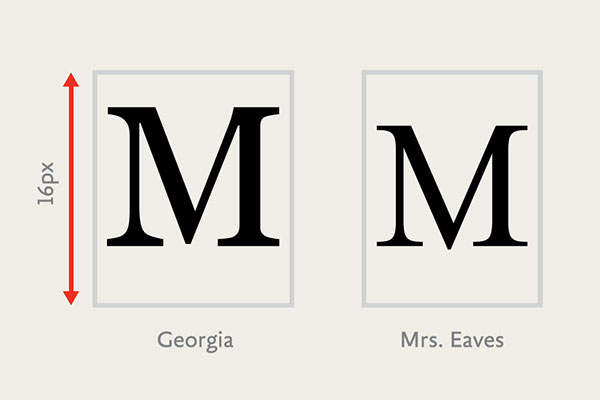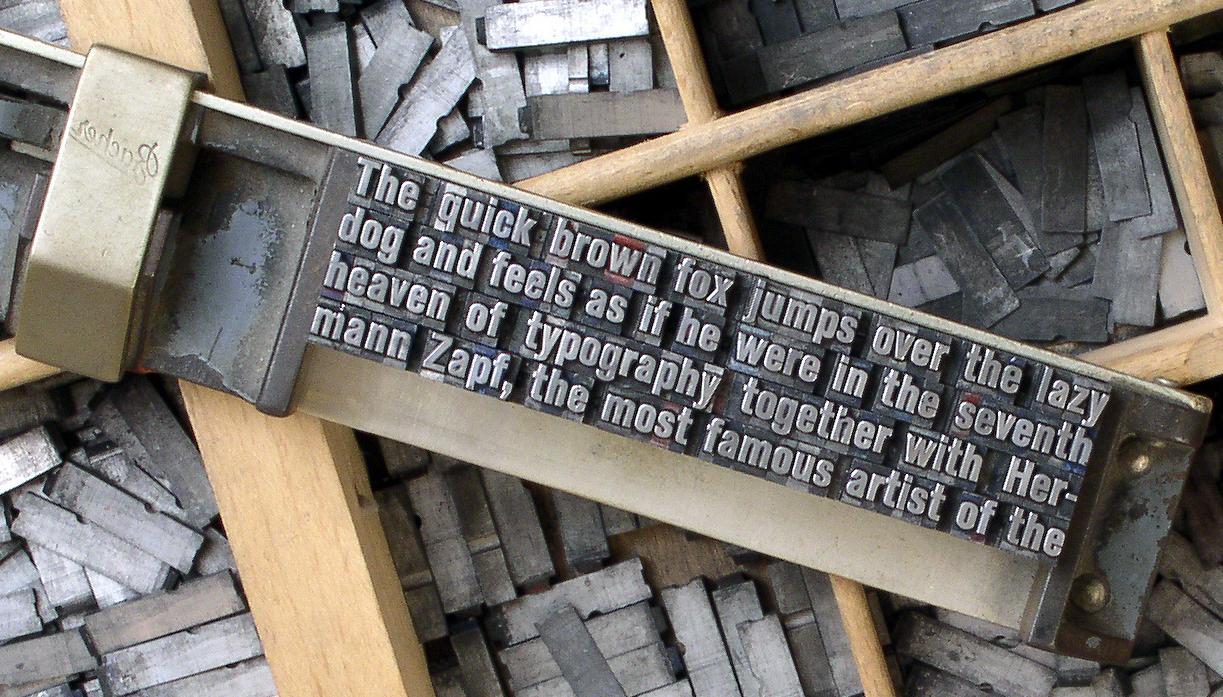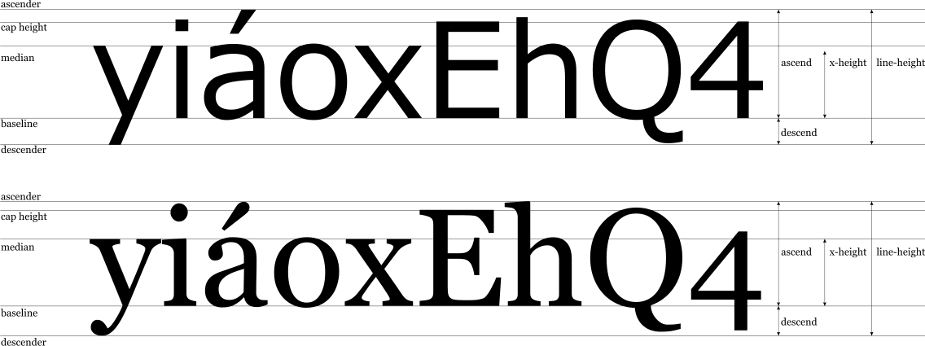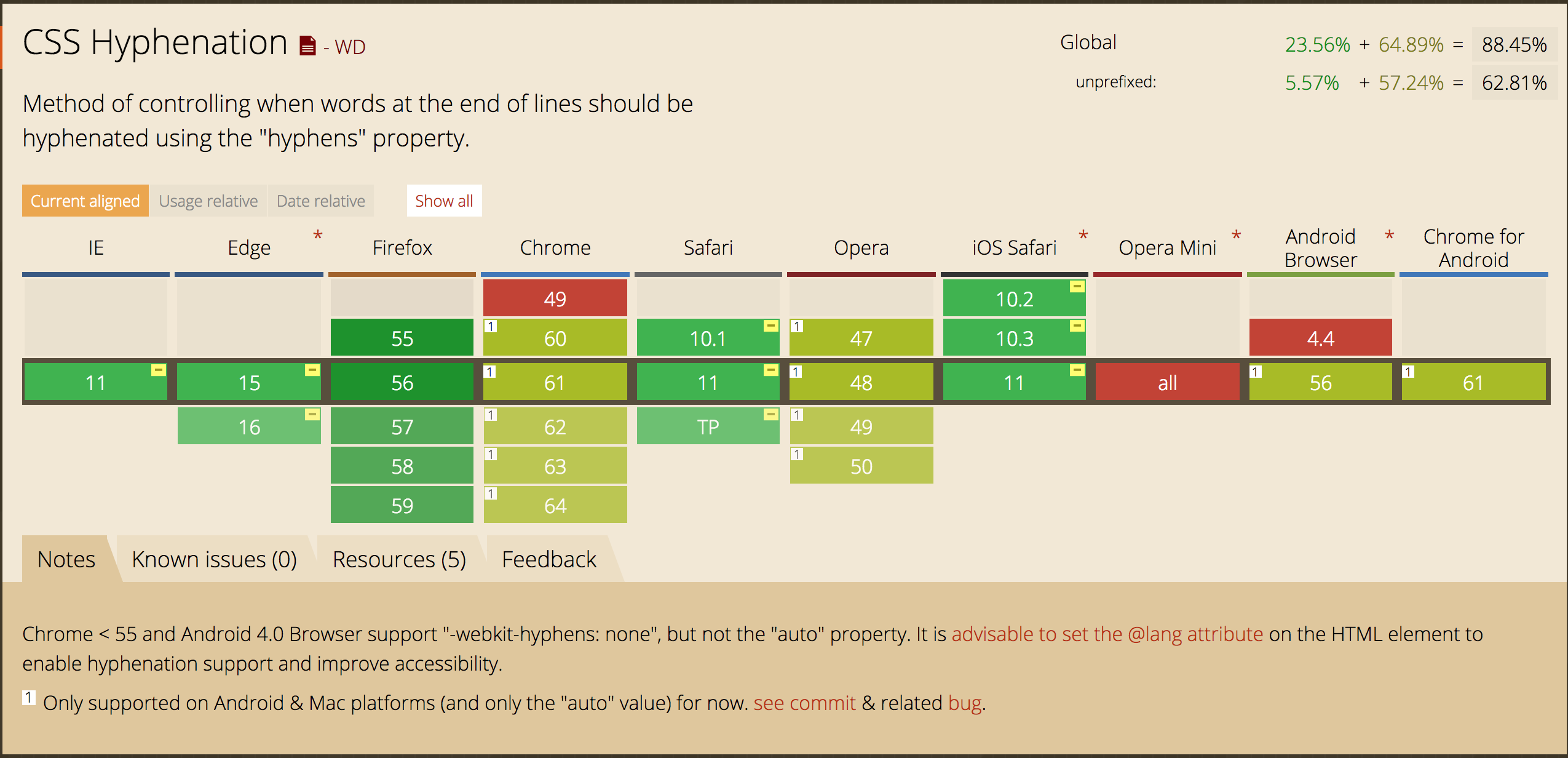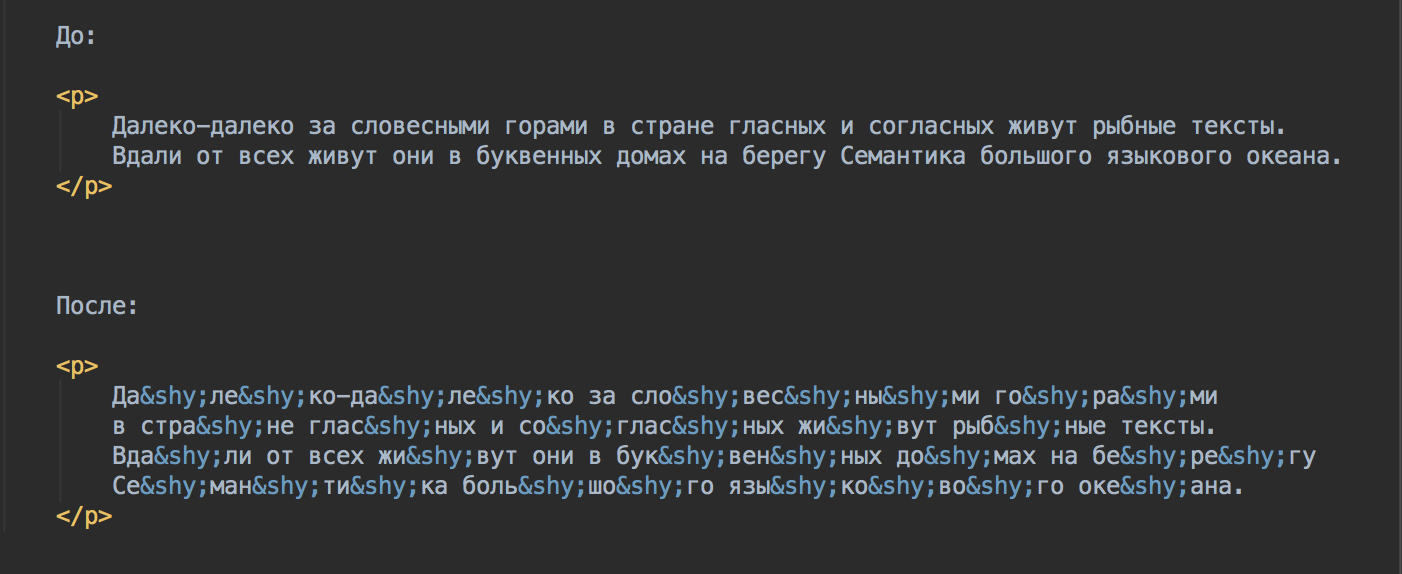
Символы могут быть различными по назначению:
векторные
Были распространены в эпоху матричных принтеров и экранов с очень маленьким разрешением и представляли собой набор растровых изображений каждого символа в виде битмапа.
Векторная графика основана на математических формулах геометрических объектов.
Современные шрифты описывают символы с помощью тех самых формул, что позволяет их масштабировать без потери качества, как и любое другое векторное изображение.
Базовая линия – воображаемая прямая линия, проходящая по нижнему краю прямых знаков без учёта свисаний и нижних выносных элементов.
Высота прописных знаков – расстояние от базовой линии до верхней линии прописных, то есть высота прописных букв без учета свисаний.
Высота строчных знаков – расстояние от базовой линии до верхней линии строчных, то есть высота строчных букв без свисаний и выносных элементов.
Интерлиньяж, межстрочный интервал — расстояние между базовыми линиями строк. В вебе данный термин чаще всего называют высотой строки.
Кегельная площадка – верхняя прямоугольная часть ножки литеры, на которой расположено выпуклое (печатающее) изображение знака.
В цифровом шрифте кегельная площадка важна при проектировании шрифта как прямоугольник, в который вписывается изображение знака.
Сравнение площадок шрифтов Perpetua и Calisto:
Гарнитура – типографский термин, объединяющий набор шрифтов, которые отличаются по размеру, начертанию, наличию или отсутствию засечек на концах линий, пропорциям символов, по соотношению размера высоты прописных и строчных знаков, величине верхних и нижних выносных элементов, плотности, то есть близких по характеру и отличительным знакам рисунка.
С помощью font-size можно определить размер шрифта элемента. Размер шрифта определяется как высота от базовой линии до верхней границы кегельной площадки.
Размер шрифта можно установить с помощью:
Первый набор значений – абсолютные: xx-small, small, medium, large, x-large, xx-large.
Более того, они зависят от
настроек браузера пользователя.
px – размер шрифта в пикселях. Так как задание динамического размера требуется нечасто, эта единица измерения является наиболее популярной.
em/% – размер шрифта в зависимости от размера шрифта родителя.
Различия между em и % могут появиться только в зависимости от настроек браузера.
pc, pt, ch, ex – типографские единицы измерения.
cm, mm, q, in – абсолютные единицы из реального мира.
vh, vw, vmin, vmax – единицы измерения относительно viewport'а.
Устанавливается двумя типами значений: единицами измерения длины или множителем. В чем же разница?
Что, если мы захотим изменить
размер шрифта у параграфов?
Для изменения данного расстояния предусмотрено
свойство letter-spacing со
значением в любой
единице измерения длины кроме процентов.
Cписок пополнился:
Хочется сделать наиболее вырвыглазный вариант, отвратный прям максимально и бесповоротно
А еще лучше – в два параграфа, чтобы вдвойне вырвиглазнее
Хочется сделать наиболее вырвыглазный вариант, отвратный прям максимально и бесповоротно
А еще лучше – в два параграфа, чтоб вдвойне вырвиглазнее